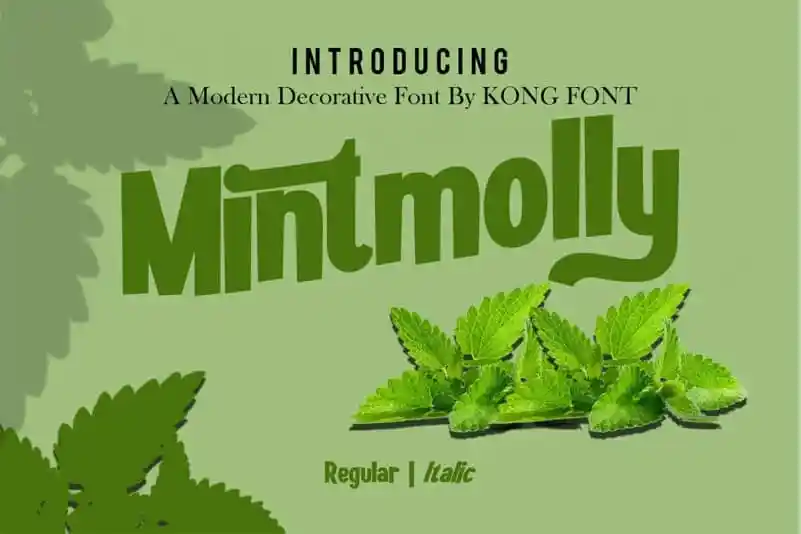
Mintmolly Display Font – Download Grátis
A Mintmolly Display Font é uma criação única para designers em busca de algo inovador no seu trabalho. Com sua proposta multipropósito, esta fonte digital se destaca como uma escolha perfeita para um design contemporâneo ou vintage. O designer da 99designs criou algo que pode ser usada em qualquer projeto, desde a criação de marcas e logos até o desenvolvimento de modelos de impressão personalizados. Composta para atender a diferentes necessidades do design, esta fonte oferece uma versatilidade única, sendo um excelente recurso para quem procura expressar seu próprio estilo no mundo digital. Não importa qual seja o projeto em questão – desde a criação de branding ou a montagem de modelos gráficos até a definição de identidades visuais, Mintmolly Display Font oferece a liberdade de criar e se expressar de maneira única.